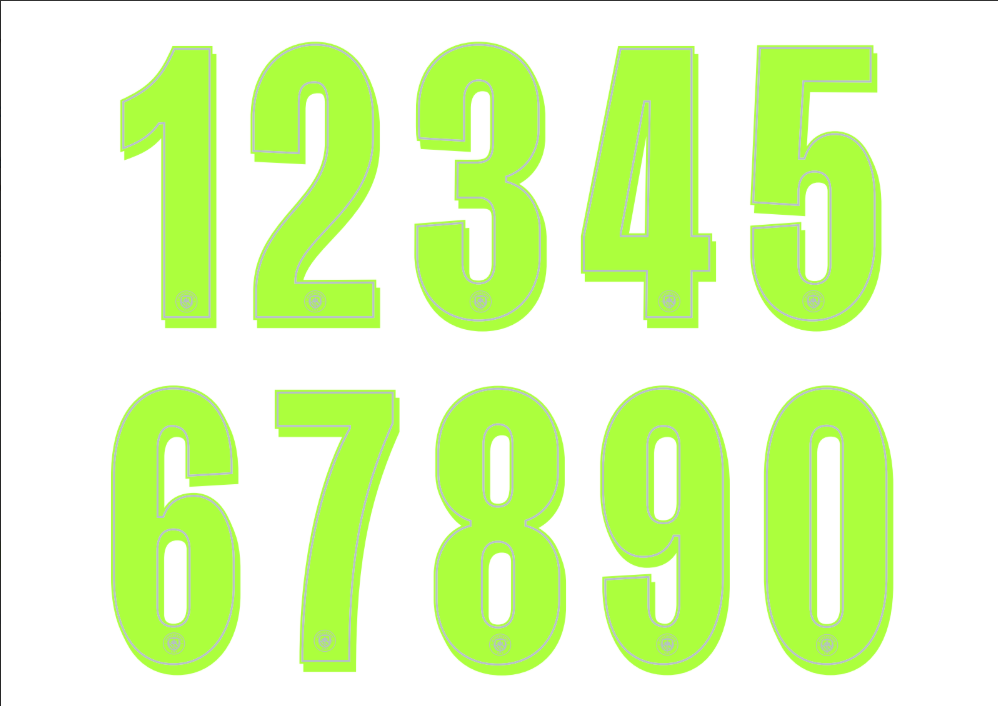
A parceria entre o Manchester City e a Puma continua rendendo frutos visuais impressionantes. Enquanto os uniformes principais mantêm a classe tradicional dos Citizens, o terceiro uniforme (Third Kit) da temporada 2025-2026 chega para quebrar padrões, trazendo uma tipografia exclusiva que reflete a modernidade e a inovação tática do time de Pep Guardiola.
Estilo Visual e Aplicação
A fonte do terceiro uniforme do Manchester City para 25/26 foge do convencional. A Puma apostou em um design futurista, com traços dinâmicos que sugerem movimento e velocidade.
Diferente da fonte padrão da Premier League, esta tipografia é exclusiva para jogos de copas internacionais e nacionais. Ela se destaca pelo contraste visual, sendo ideal para aplicações em camisas de cores vibrantes ou escuras, típicas dos uniformes “Third”. É a escolha perfeita para criar mockups de camisas alternativas ou estampar nomes de craques como Haaland e Foden em produtos personalizados.
Dica de Designer: Para um resultado profissional na sublimação, utilize contornos (strokes) na cor secundária do uniforme para destacar a numeração, conforme o padrão oficial de jogo.